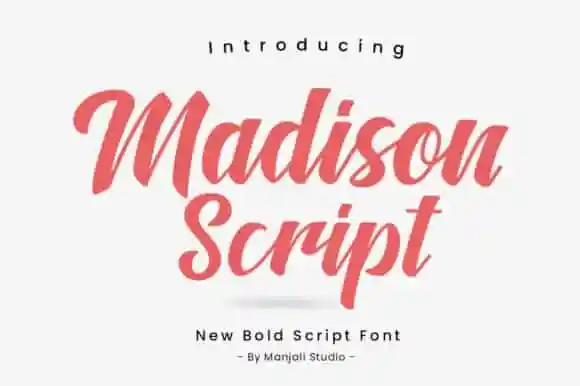
A Madison Script Font é uma deliciosa escolha para aqueles que buscam adicionar um toque elegante à suas criações digitais. Com sua textura natural e estilo artesanal, essa fonte script não só renovará seu próximo projeto de design como também o deixará com um aspecto autêntico. Desenvolvida pelo Manjalistudio e disponibilizada pela 99designs, a Madison Script Font é uma opção perfeita para quem aprecia os elementos de gráfica clássicos misturados com um toque moderno e atual. Permanecendo fiel às influências da caligrafia enquanto também mantém um ar contemporâneo, essa fonte traz um encanto único que pode transformar qualquer projeto em algo verdadeiramente especial. Engane-se, e permita-se ser seduzido por esse design excepcionalmente refinado, capaz de levantar seu trabalho a níveis inacreditáveis.